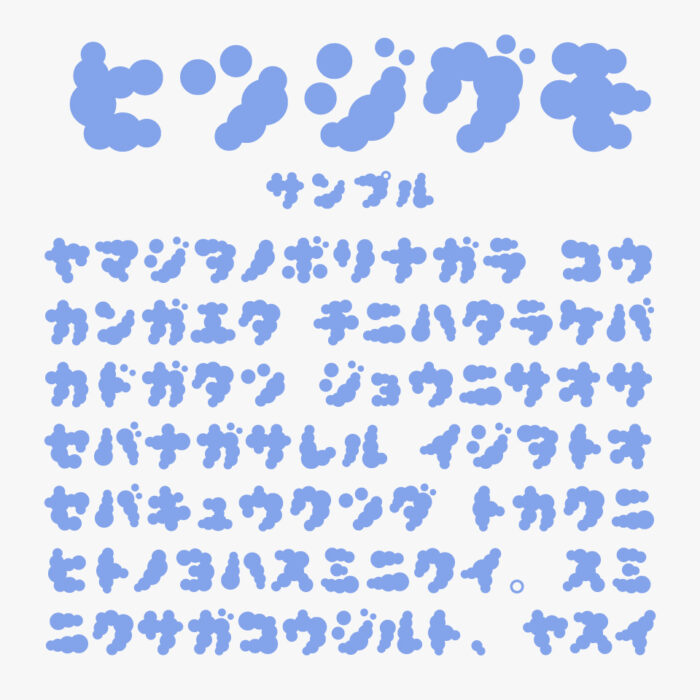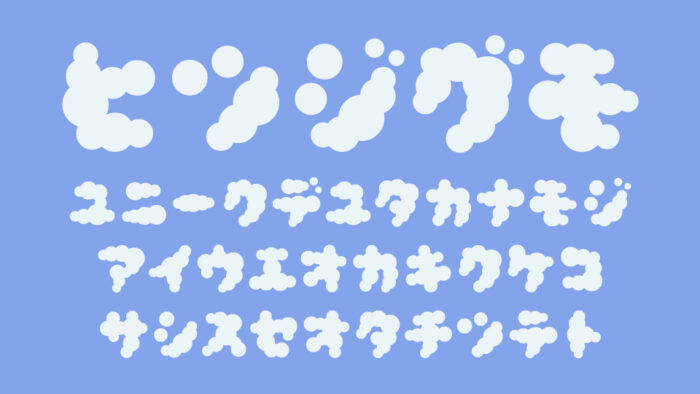
ヒツジグモフォントは、ふわふわとした雲のように見えるユニークで遊び心のあるカタカナフォントです。
丸いドットで文字が構成され、ひとつひとつの字が泡のように連なって雲のようなフォルムとして形作られています。濁点などは丸いドットのみで表現されているのがとっても可愛らしいです。
収録文字は、カタカナ・記号が収録されています。